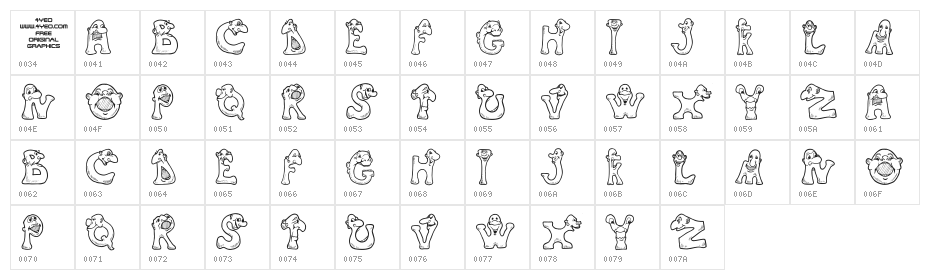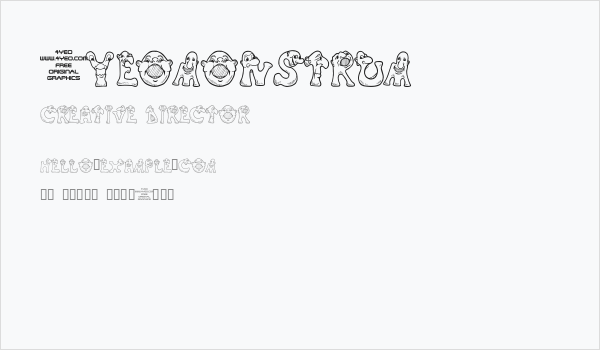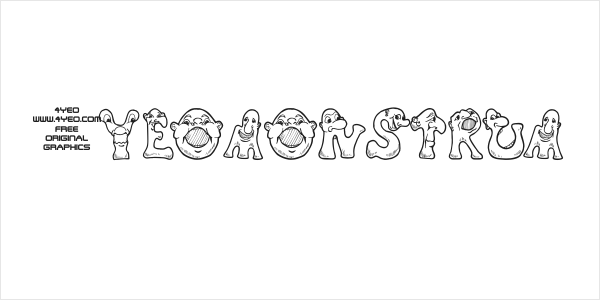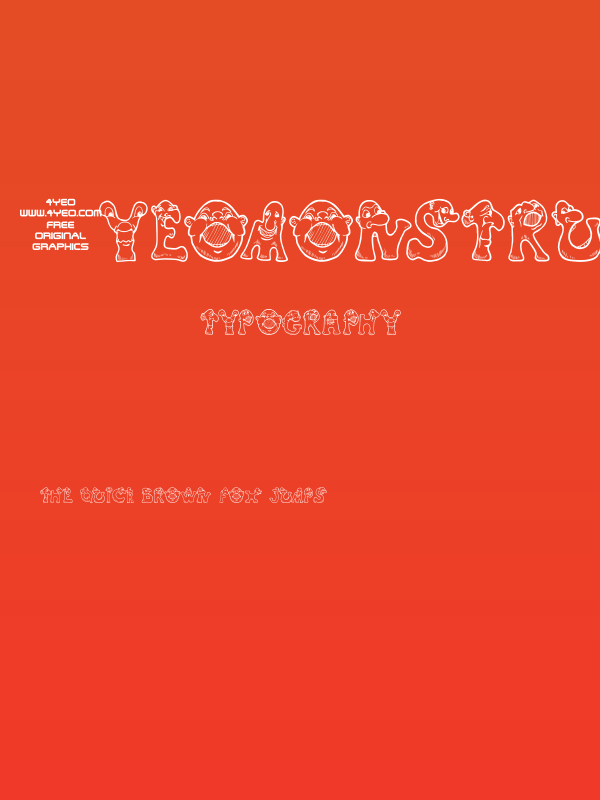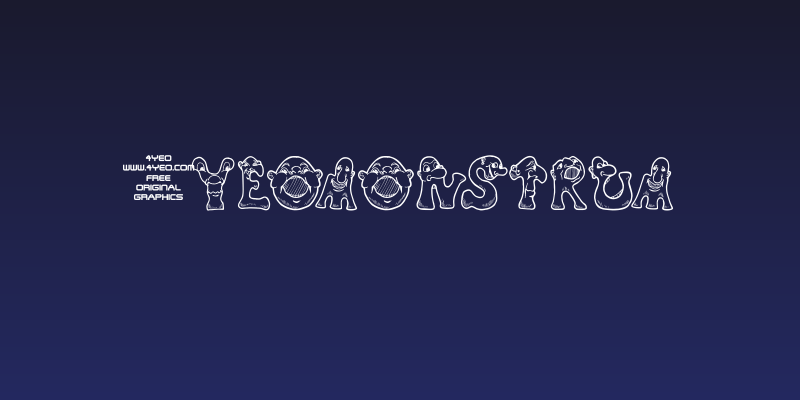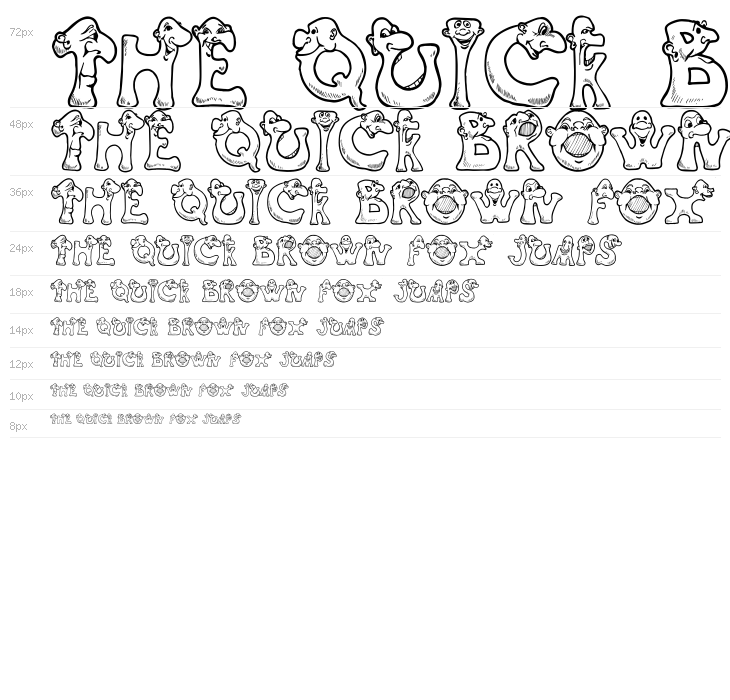
4YEOmonstrum Font
| Style général | Playful, Whimsical, Decorative |
| Projets proposés | Ideal for children's books, playful branding, party invitations, and creative posters. |